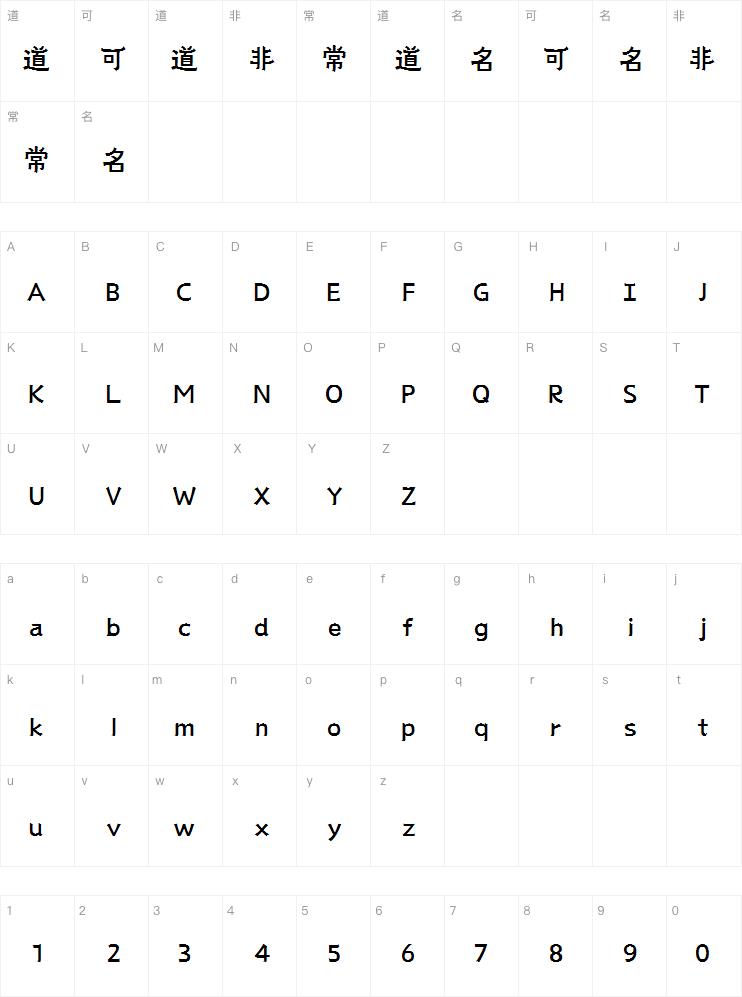
山海魏碑隶黑65W,是一款全新隶书+黑体风格的字体,是山海魏碑隶黑字体家族系列中的常规粗细款,编号65W,包含汉字9169个,符号200+个。该字体是一款具有强劲视觉冲击力的隶书+黑体风格的字体。字形结构多为方形结构,如正方形、长方形或扁方形,强调字形的稳定性和内敛精神。字形大小悬殊,通过大小不一的字来形成对比和层次感,造型硬朗,直线与曲线结合的笔画构成棱角分明、坚实有力。